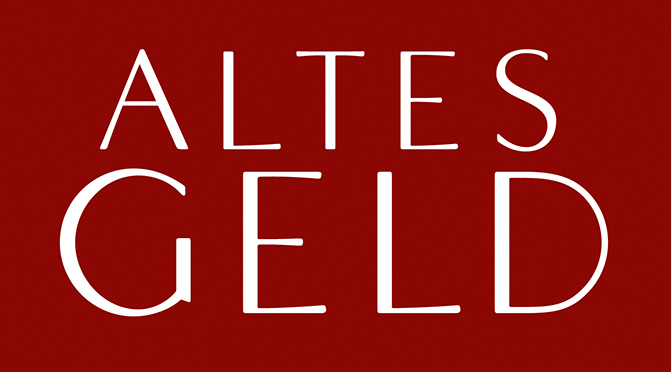
Florida (Hans Karl Gustav Möhring) wurde für die Titel der Filme Persona (Ingmar Bergman) und Altes Geld (David Schalko) verwendet. Weiß jemand, ob die Schrift digitalisiert wurde? Der Verdacht liegt nahe, weil sie auch für den Abspann von Altes Geld gewählt wurde.
Soweit ich sehe, gibts die aber nicht als digitale Version.
Die Vinter kommt aber nah dran.
Danke, aber die beiden Vorschläge weichen mir zu sehr ab. Ein paar Buchstaben der Florida hatte ich schon mal nachgezeichnet – vielleicht mache ich ja auch noch den Rest.
Nur ein Schnitt, also den Originalschnitt, nur die Großbuchstaben wie im Original würde doch sehr weit reichen? Warum eine ganze Familie? Warum gemin werden? Wäre das was für die SIL-OFL? Damit wäre auch die Anpassung an die verschiedenen Sprachen schon mal möglicher und Du könntest Dir einiges an Arbeit ersparen?